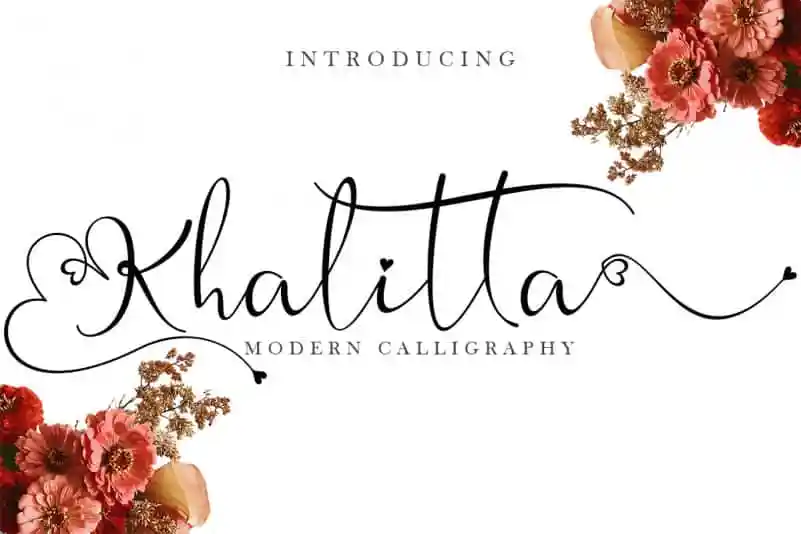
Khalitta Calligraphy Font – Download Grátis
A fonte Khalitta Calligraphy é perfeita para qualquer tipo de trabalho que você possa imaginar. Desenvolvida pelo designer Yoga Letter, ela se destaca por sua elegância e beleza. Esta font é perfeitamente adequada para um leque amplo de aplicabilidades criativas. A Khalitta Calligraphy traz a modernidade do calligrafia em um formato digital que pode ser utilizada sem limitações. Suas linhas finas e detalhes precisos permitem uma variedade imensa de possibilidades, desde criações para casamentos até identidades empresariais ou logos. Ela também é perfeita para se integrar aos status das redes sociais, permitindo que você capture momentos românticos com um toque autêntico e elegante. Seja para criar um anúncio para seu negócio, uma marca memorável ou apenas expressar sentimentos mais íntimos em sua rede social, a Khalitta Calligraphy está aqui para tornar tudo mais especial. Não importa o tamanho do projeto, este é um chamado à fazer as coisas belas e únicas com a Khalitta Calligraphy Font.